Bộ font thư pháp được tuyển chọn để bạn thiết kế và soạn thảo như những ông đồ thời nay, với những mẫu chữ thư pháp độc đáo, đa dạng chắc chắn sẽ khiến bạn hài lòng. Cùng xem những bức vẽ dưới đây trước khi tải trọn bộ font thu phap từ Fontchu.com. Link tải font ở cuối bài viết
Ai yêu ghét chẳng bận lòng. Duỗi chân nằm ngủ thong dong bên đời
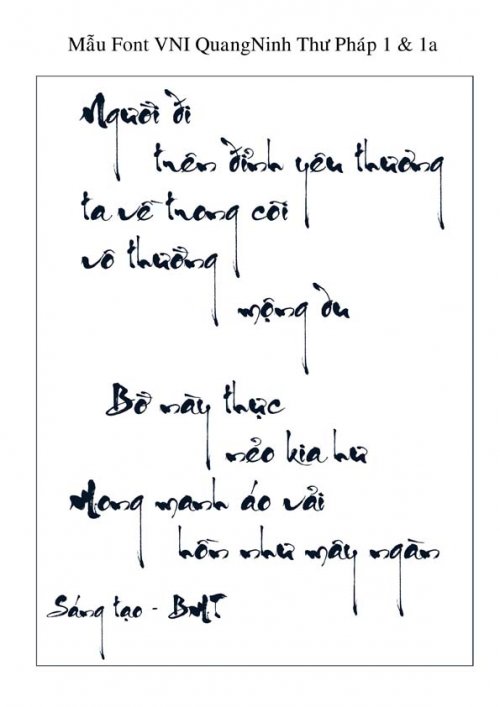
Người đi trên đỉnh yêu thương. Ta về trong cõi vô thường mộng du. Bờ này thực nẻo kia hư. Mong manh áo vải hồn như mây ngàn